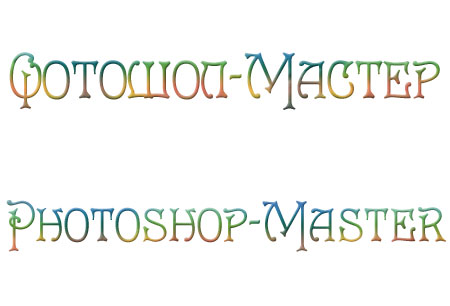
Создатель хорош)
Афигенно :)
Спасибо! Классный шрифт!
Классный шрифт, СПАСИБО!
Отличный шрифт!!! Спасибо!
Классно!
Симпотично=)))
Радужное такое)веселенькое)